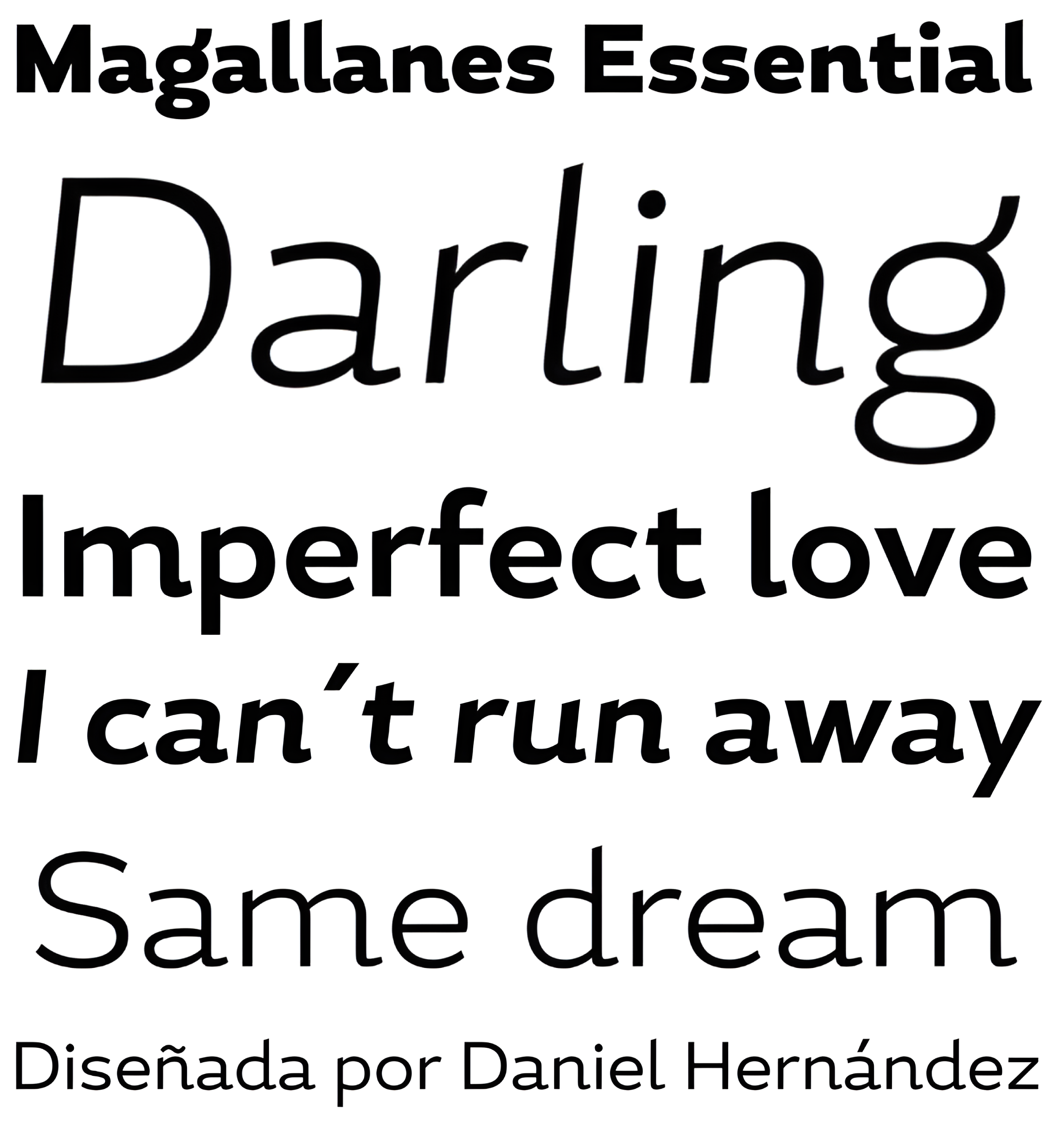
| Año | 2012 |
| Créditos | Danie Hernández |
| Descripción | Magallanes Essential es una fuente sin gracias neohumanista contemporánea diseñada por Daniel Hernández. Sus trazos y terminales están relacionados con los trazos caligráficos de las tipografías humanistas. Cada peso viene con glifos alternativos para un uso más dinámico. Magallanes es la fuente de titulación perfecta para complementar caras de texto en revistas, logotipos, etc. Es una familia esencial de 8 fuentes, 4 pesos y cursiva. Este tipo de letra no contiene glifos alternativos y sólo añade el juego de caracteres Windows 1252 (219 glifos). |
| Familia(s) | Light, Light Italic, Regular, Regular Italic, Bold, Bold Italic, Black, Black Italic |
| Estilos | 8 |
| Fundidora | Los Andes |